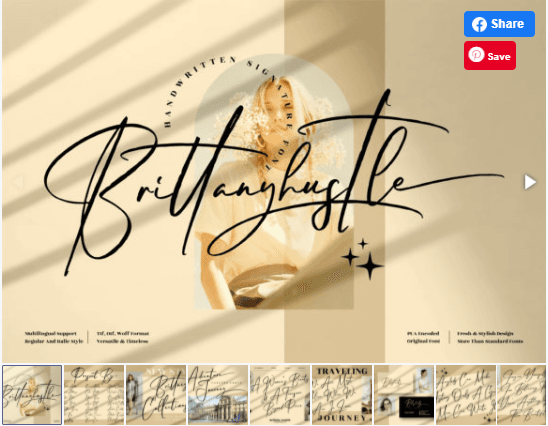
Brittanyhustle Font
Brittanyhustle - модный и нежный рукописный шрифт. Изящный и стильный, этот шрифт идеально подойдет для написания свадебных приглашений, открыток или любого другого дизайна, который может потребовать романтического, индивидуального подхода!